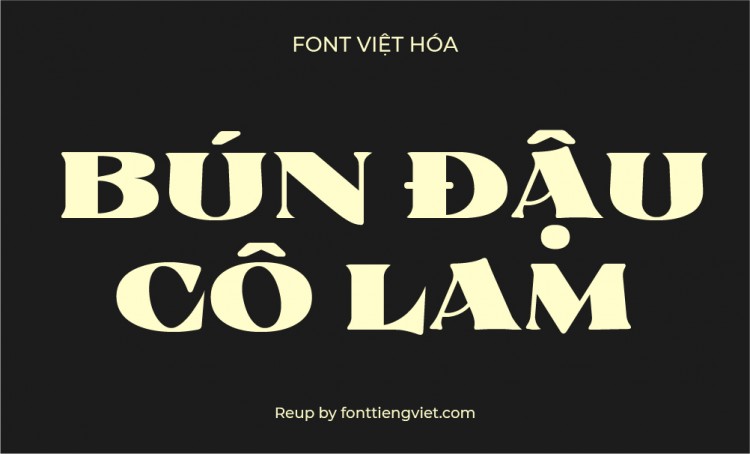
Font việt hóa MJ Rochek Display
Giới thiệu về Font việt hóa MJ Rochek Display trong thiết kế đồ họa
Trong thế giới sáng tạo hiện nay, việc lựa chọn một bộ Font Miễn Phí chất lượng luôn là ưu tiên hàng đầu của các nhà thiết kế. Font việt hóa MJ Rochek Display nổi lên như một hiện tượng nhờ sự kết hợp hoàn hảo giữa nét hiện đại và phong cách cổ điển đầy tinh tế. Đây là một bộ font thuộc thể loại Display, được thiết kế đặc biệt để thu hút ánh nhìn ngay từ giây phút đầu tiên. Phiên bản việt hóa giúp người dùng tại Việt Nam dễ dàng ứng dụng vào các dự án truyền thông mà không lo lỗi dấu hay thiếu ký tự đặc trưng. Đối với các bạn học sinh và sinh viên, việc sử dụng bộ chữ này sẽ giúp bài thuyết trình hoặc báo cáo thực hành trở nên chuyên nghiệp và bắt mắt hơn rất nhiều.
Những đặc điểm nổi bật của Font việt hóa MJ Rochek Display
Phong cách thiết kế mạnh mẽ và sang trọng
Đặc trưng lớn nhất của Font việt hóa MJ Rochek Display chính là những đường nét dày dặn, dứt khoát nhưng không kém phần uyển chuyển. Các chữ cái được tạo hình với độ tương phản cao giữa nét thanh và nét đậm, tạo nên một cấu trúc thị giác vô cùng vững chãi. Chính nhờ sự độc đáo này, font chữ thường được ưu tiên sử dụng cho các tiêu đề lớn, bìa sách hoặc các bảng hiệu quảng cáo cần sự nhận diện nhanh chóng. Sự tỉ mỉ trong quá trình việt hóa đảm bảo rằng các dấu thanh như huyền, sắc, hỏi, ngã, nặng được đặt ở vị trí cân đối, giữ nguyên linh hồn của bản thiết kế gốc.
Khả năng ứng dụng đa dạng trong nhiều lĩnh vực
Dù mang hơi hướng Display nhưng Font việt hóa MJ Rochek Display lại tỏ ra cực kỳ linh hoạt. Bạn có thể sử dụng nó để làm logo cho một quán cà phê phong cách Retro, thiết kế thiệp mời sự kiện sang trọng hoặc đơn giản là tạo ra những hình ảnh trích dẫn đầy cảm hứng trên mạng xã hội. Trong môi trường học đường, giáo viên có thể dùng font chữ này để trang trí bảng tin hoặc làm tiêu đề cho các slide bài giảng nhằm tăng tính thẩm mỹ và khơi gợi hứng thú học tập cho học sinh. Khả năng hiển thị sắc nét trên cả màn hình kỹ thuật số và bản in truyền thống là một điểm cộng lớn giúp bộ font này chiếm trọn niềm tin của cộng đồng thiết kế.
Lợi ích khi sử dụng Font việt hóa MJ Rochek Display cho dự án của bạn
Kết luận về giá trị của Font việt hóa MJ Rochek Display